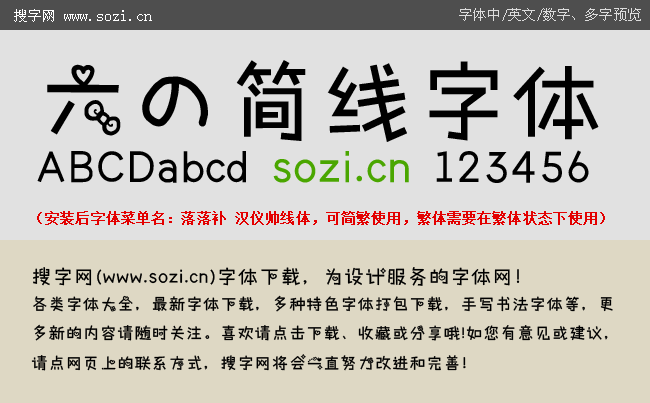
六の簡線字體
搜字網(wǎng)給大家提供一款俏皮可愛的手機中文字體下載。修改者叫它六の簡線字體,這款手機字體是在漢儀帥線體筆畫間插入了卡通圖案。漢儀帥線體運用平頭和直線描繪,筆畫設(shè)計上硬朗,部件設(shè)計上有棱角、直接。力求現(xiàn)男孩子直率的性格。字與字之間依據(jù)字本身結(jié)構(gòu)特質(zhì)有大小變化,營造跳躍和俏皮之感。使整體形象不呆板。加入了卡通圖案后又增添了趣味性,特別適合喜歡手機字體個性一些的朋友在手機上安裝使用。